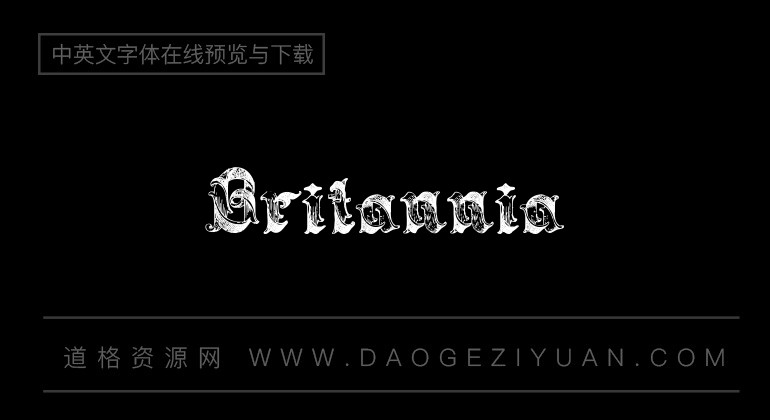
Britannia 字体是一种古典文艺复兴风格的英文字体,由英国著名的设计师William Caslon IV于1817年设计,主要用于书籍装帧和报刊印刷。它的字体特点是字母的高度和宽度均衡,字母的笔划宽而粗,具有古典的美感。它的字体风格比较传统,适用于正式的文件、书籍以及其他文字制作,可以给文字带来经典的气息。内容介绍
Britannia是一款非常不错的手写艺术字体,具有很好的视觉感,适合于文化类的宣传设计、商业类品牌的广告和产品包装设计以及个性化文字排版等较多场景。